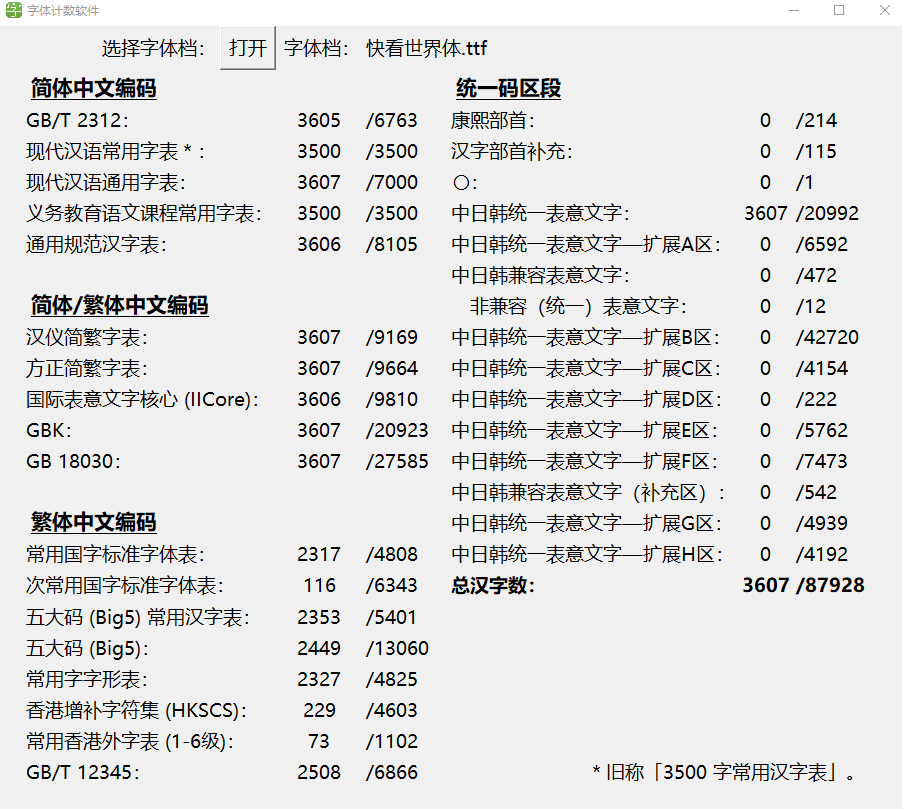
快看世界体:快看KKDC出品免费商用艺术字体
字体作者:冷水萧 (中国大陆) 字体字重:1个
这款字是我第一款从设计-封装-测试全部自己完成的字库
快看世界体由快看KKDC出品,字体设计以漫画中的对话框元素为起点,
融入快看ACGN文化,年轻潮流,大胆有态度。
字体特点末端尖角,中宫外扩、字面瘦长、倾斜8度;包含6763个字。
Ver 1.4(2023/12/13)
• 字体数已达6765个字
Ver 1.3(2023/10/09)
• 字体数已达6192个字
Ver 1.2(2023/07/05)
• 新增1880个汉字
Ver 1.2(2023/03/21)
• 修复错字“差”
Ver 1.1(2023/03/02)
• 快看世界体正式发布🎉
这个字体非常棒,免费字体里前三。
2024.1.03留言:缺少”垚“字。
字体有错别字,差别的差,永远打出来都是着
快看世界体:美元符号 $ 缺失
这个字体缺字有点多,连GB2312都不能完整支持
• 只支持新 3500 常用字(通规表一级字)外加 1 个字
这个字体看起来很酷,但是我觉得原作者是想加上台湾和日本使用的繁体字。 (如果会韩文就更好了)